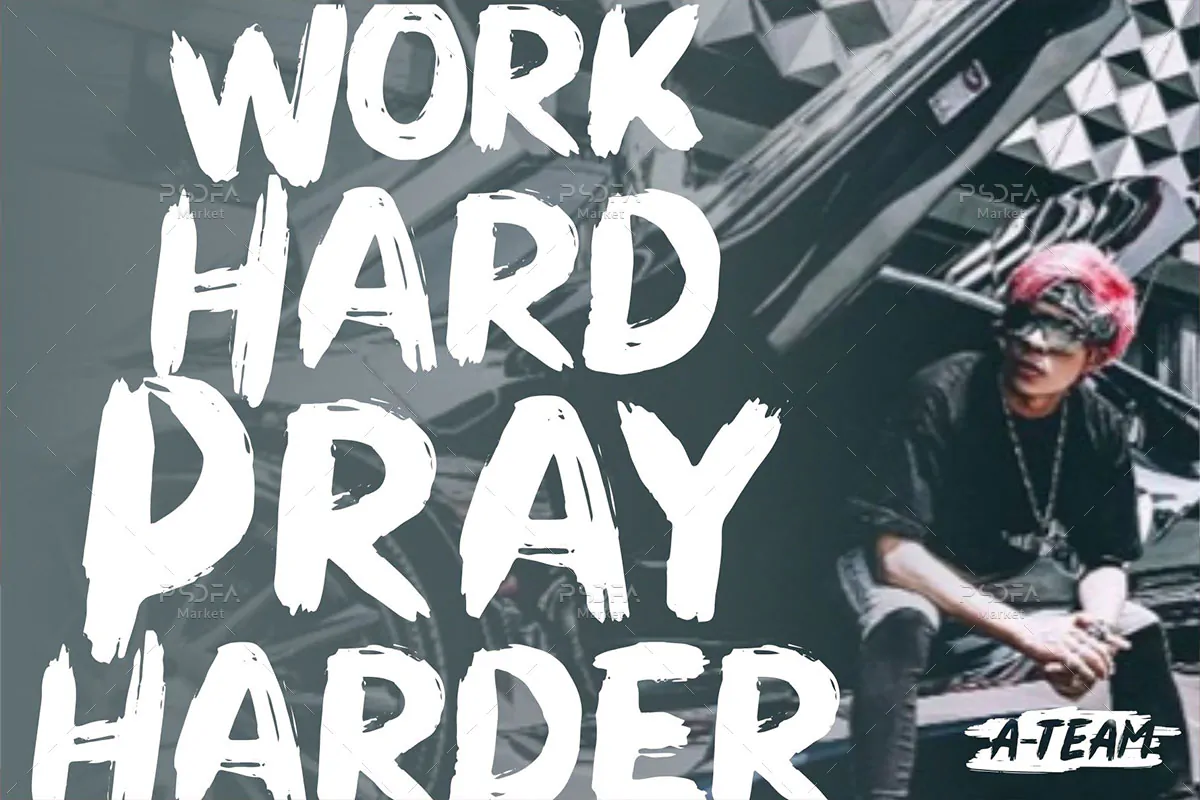
فونت قلمویی کثیف Dirty Brush یک قلم انگلیسی فوق العاده زیبا است که مناسب جهت استفاده در طرح و پروژههای گرافیکی مختلف میباشد. این فونت زیبا با وزن معمولی طراحی شده است که میتوانید از آن در طراحی انواع پوستر، کارت ویزیت، بروشور، تراکت، تقویم، کاور موزیک و … استفاده کنید.